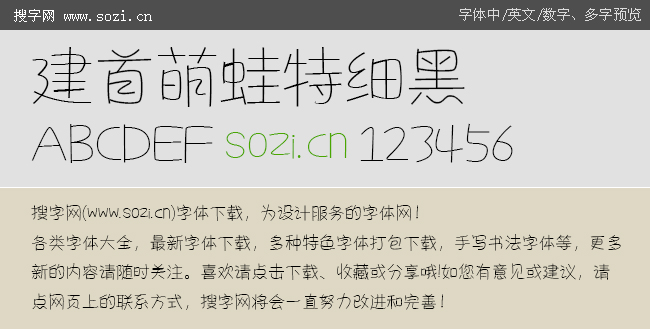
建首萌蛙特細(xì)黑
搜字網(wǎng)提供一款建首萌蛙特細(xì)黑中文字體下載,建首萌蛙特細(xì)黑是一套卡通風(fēng)格的POP字體。字體筆畫(huà)簡(jiǎn)潔醒目,字形為卡通風(fēng)格,充滿童趣,看上去非?蓯(ài)。適合兒童包裝設(shè)計(jì)、海報(bào)設(shè)計(jì)、廣告設(shè)計(jì)等應(yīng)用。